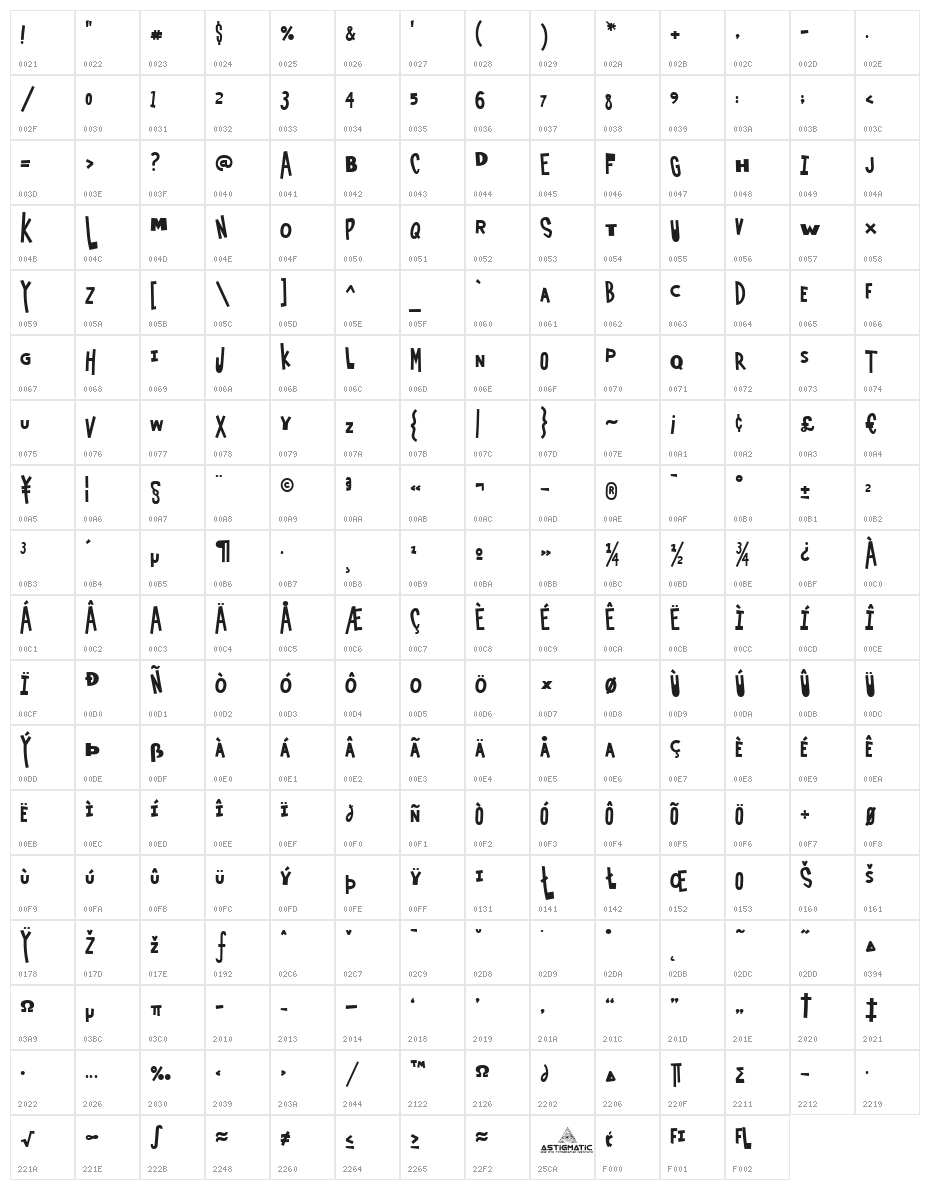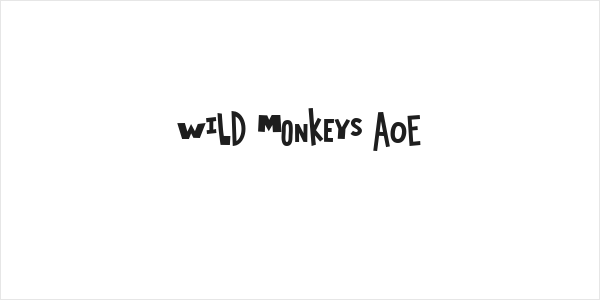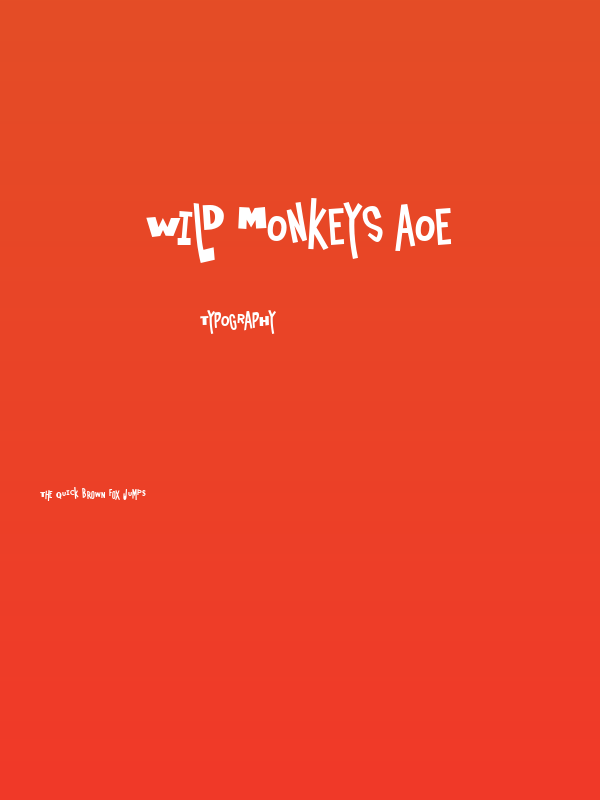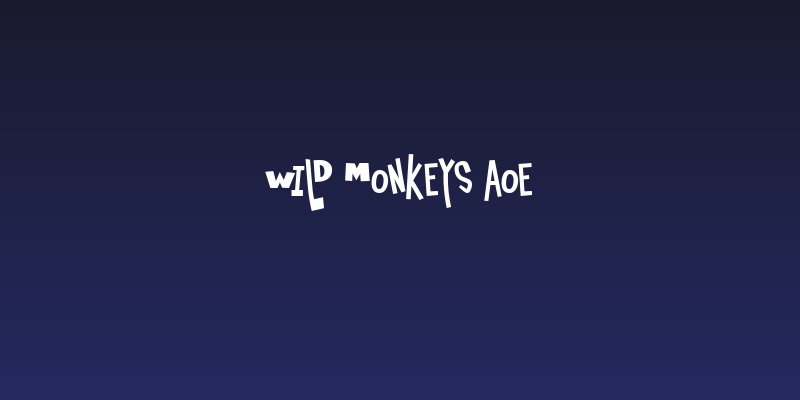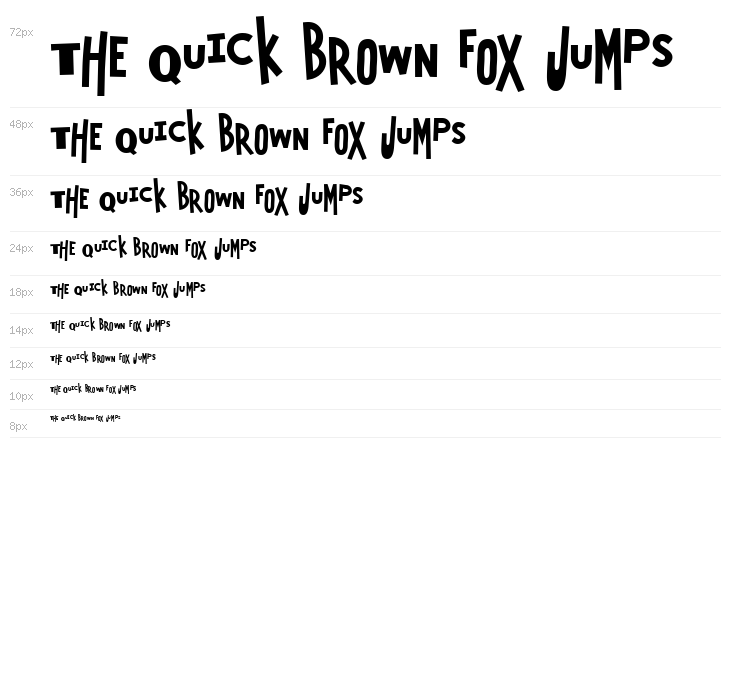
Wild Monkeys AOE Font
✎ Comic
| Estilo general | Playful |
| Proyectos propuestos | Ideal for children's books, comic strips, playful branding, party invitations, and creative posters. |